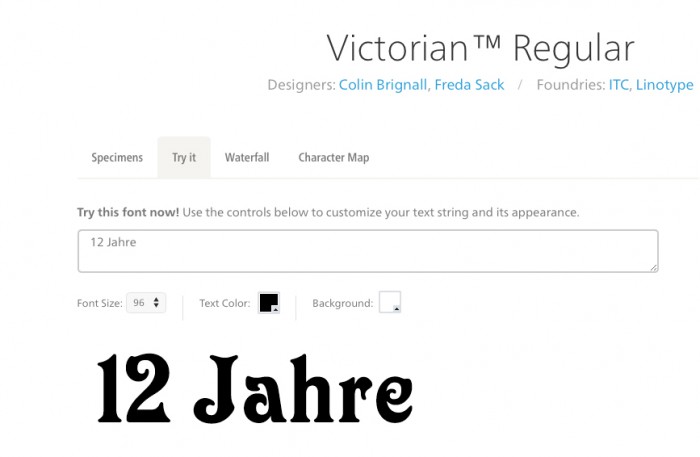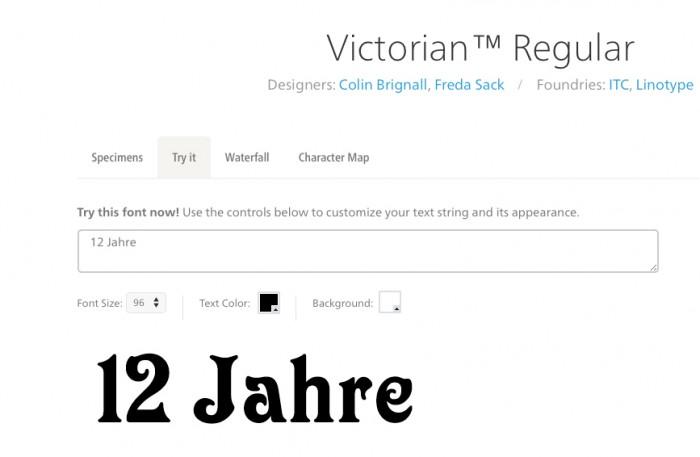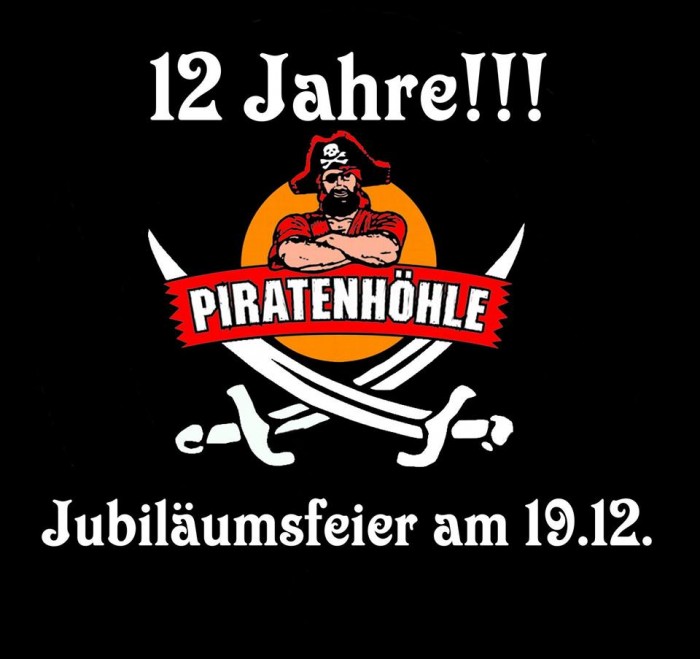
Schriftart auf einem Flyer
ich würde gerne wissen, um welche Schriftart es sich beim angefügten Bild handelt. Ich beziehe mich nur auf folgenden Text: "12 Jahre!!! Jubiläumsfeier am 19.12."
wer kennt eigentlich die angeknabberte ITC-Machine (Piratenhöhle)? Oder war das kurze Handarbeit? Glaub ich aber fast nicht ... aber ich finde die Schrift gerade wirklich nicht ... *rotwerd*